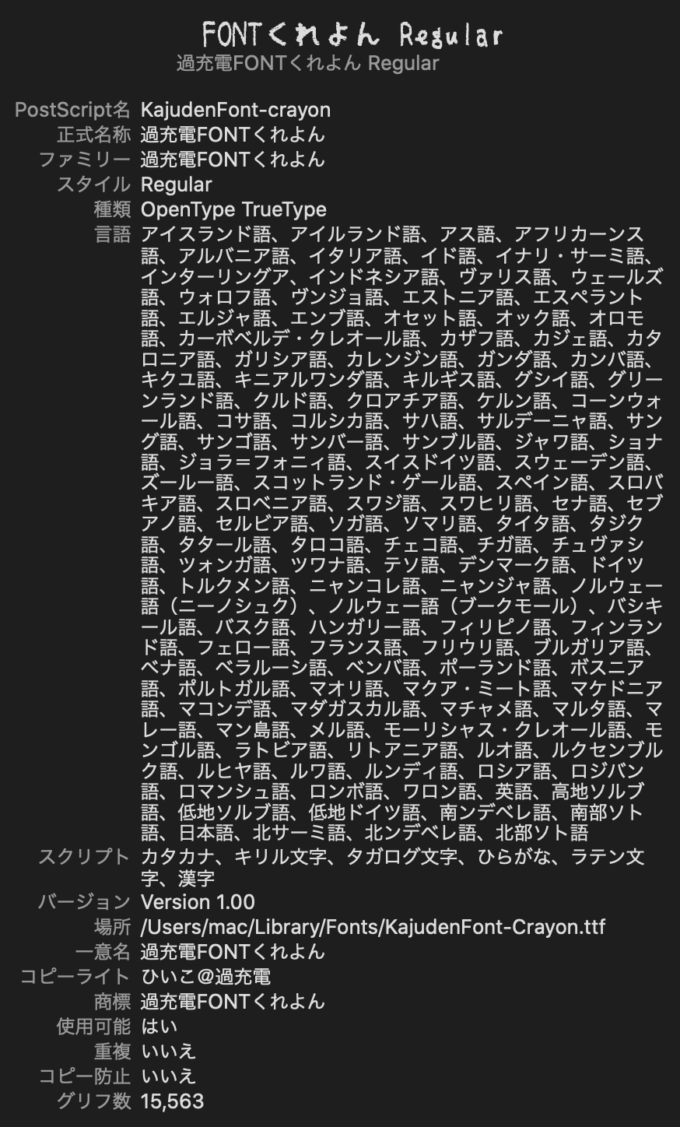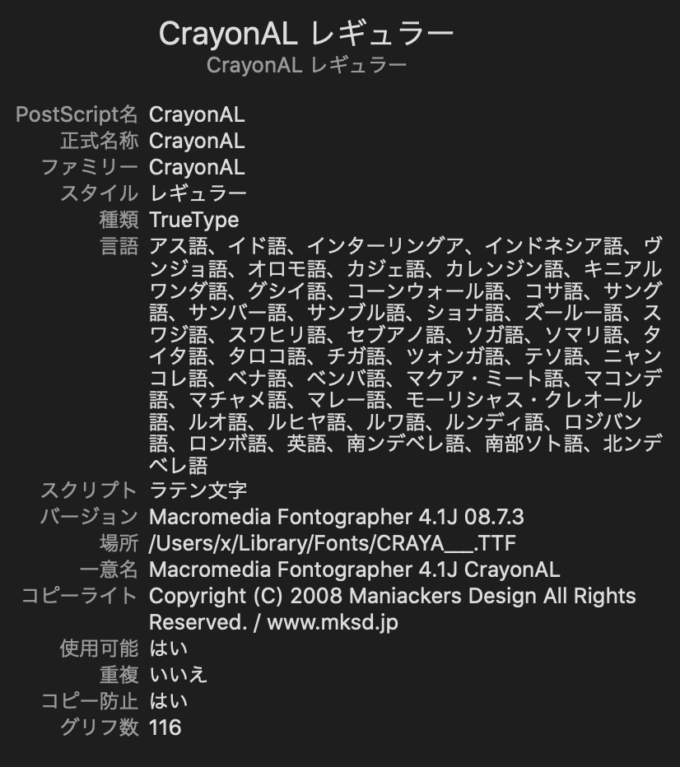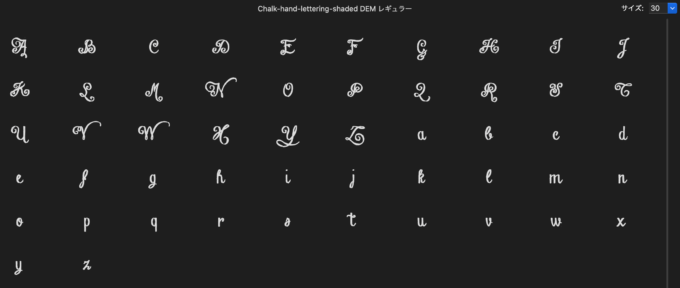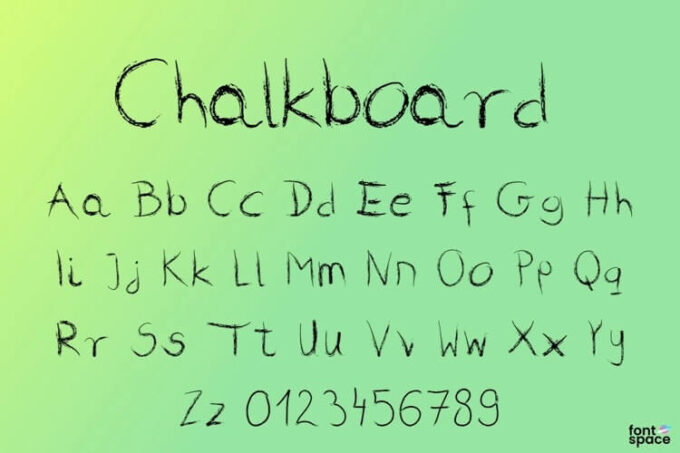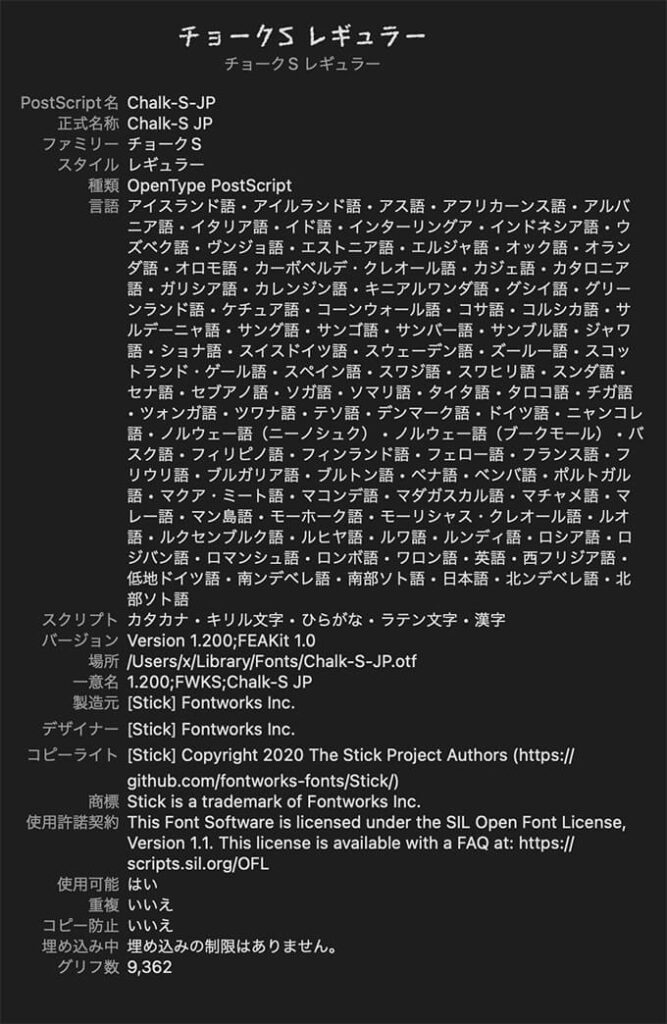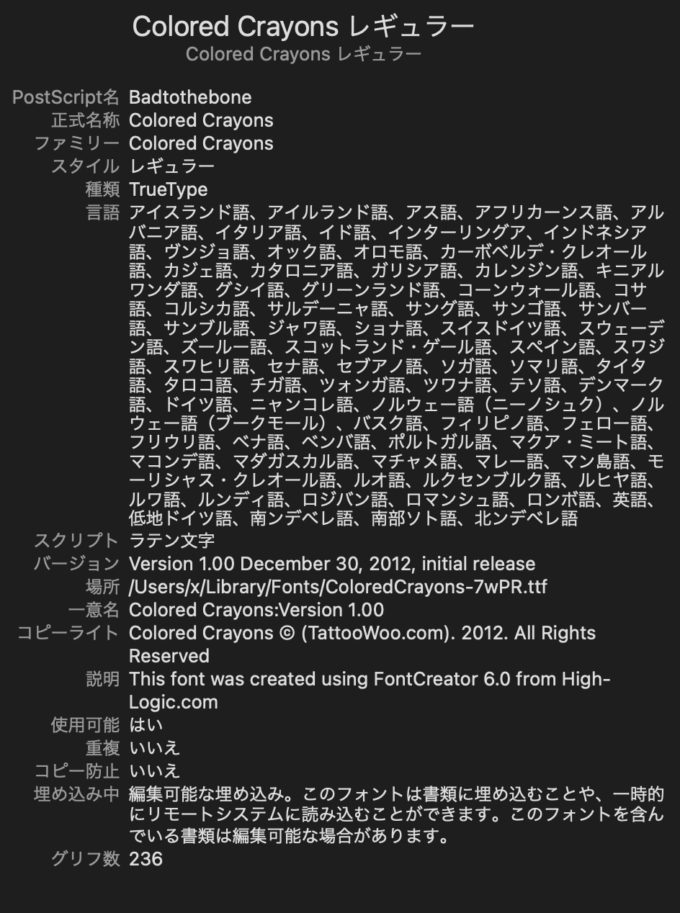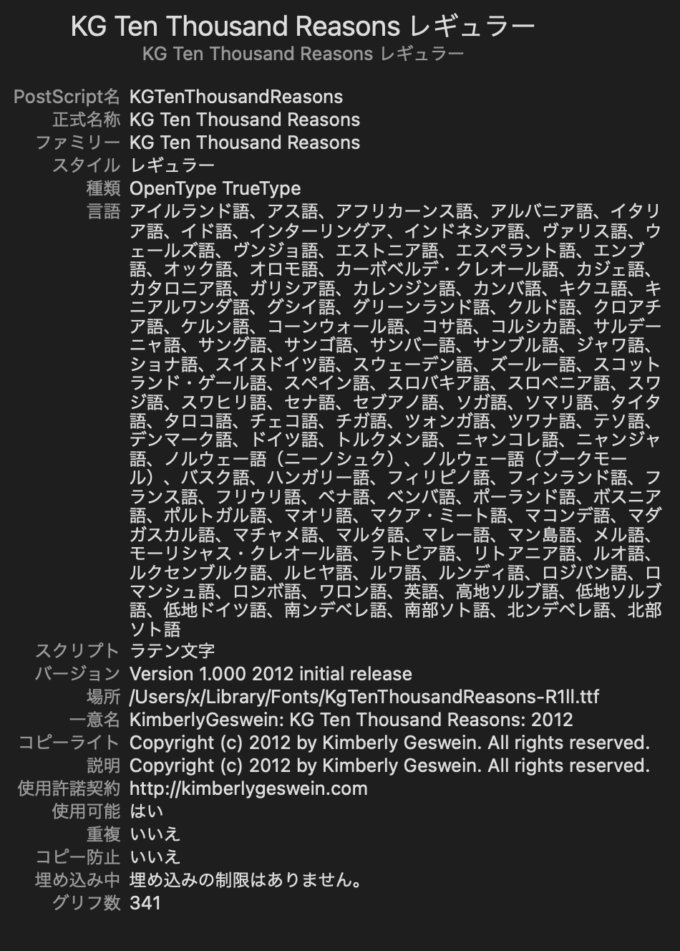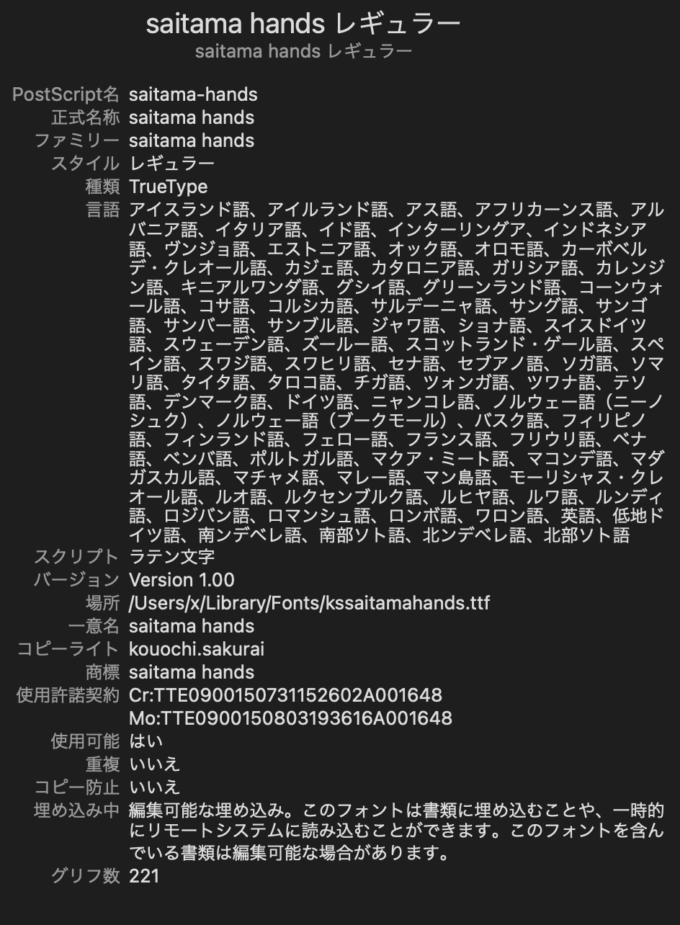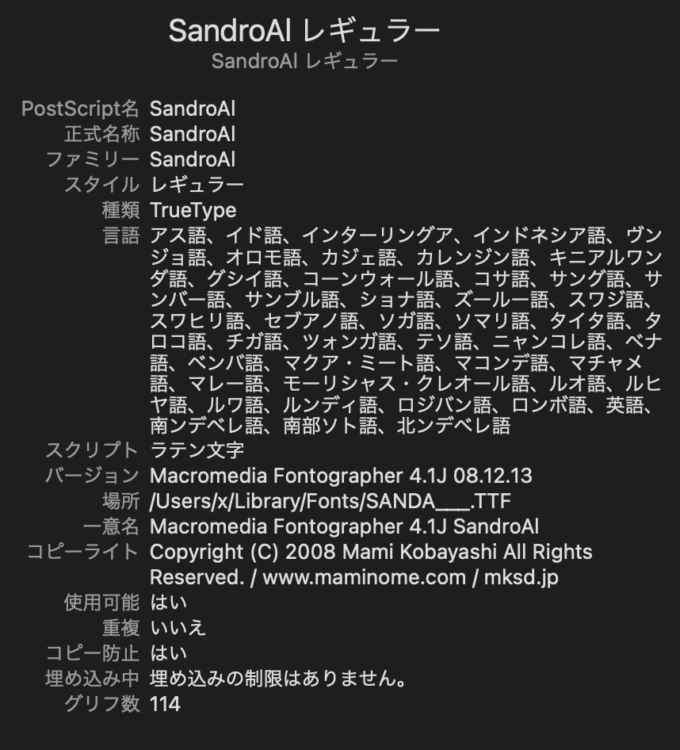
全て無料!!クレヨンで描いたような『クレヨンフォント素材』
今回はクレヨンで描いたような表現ができる『クレヨンフォント素材』を紹介していきます。
クレヨン・アルファベット
ちはやクレヨンRE
Chalkboard Font
殴り書きクレヨン
埼玉ハンズ
過充電FONTくれよん
Colored Crayons
Chalk Hand Lettering Shaded
ピンポンフォント
KG Ten Thousand Reasons Font